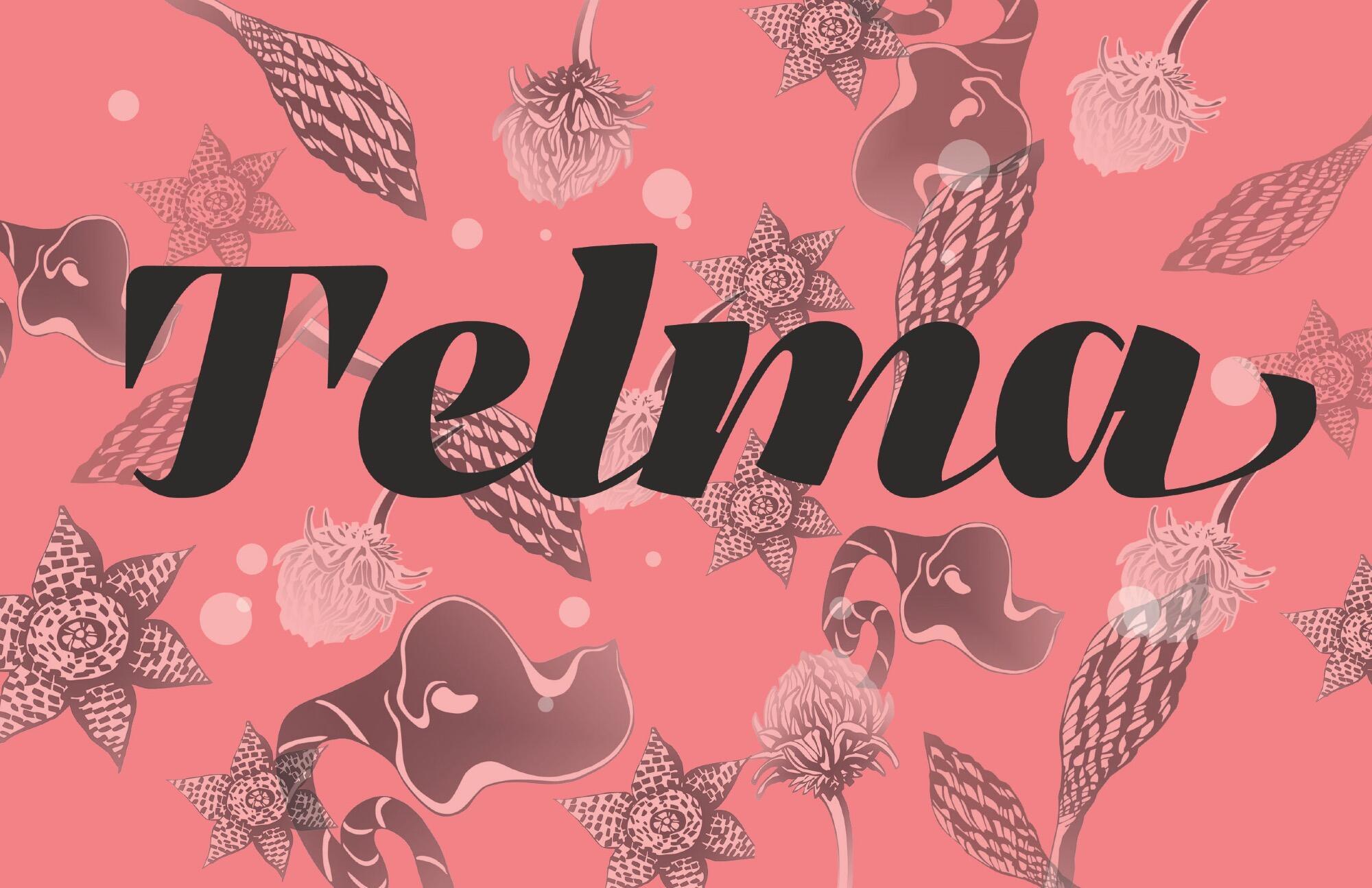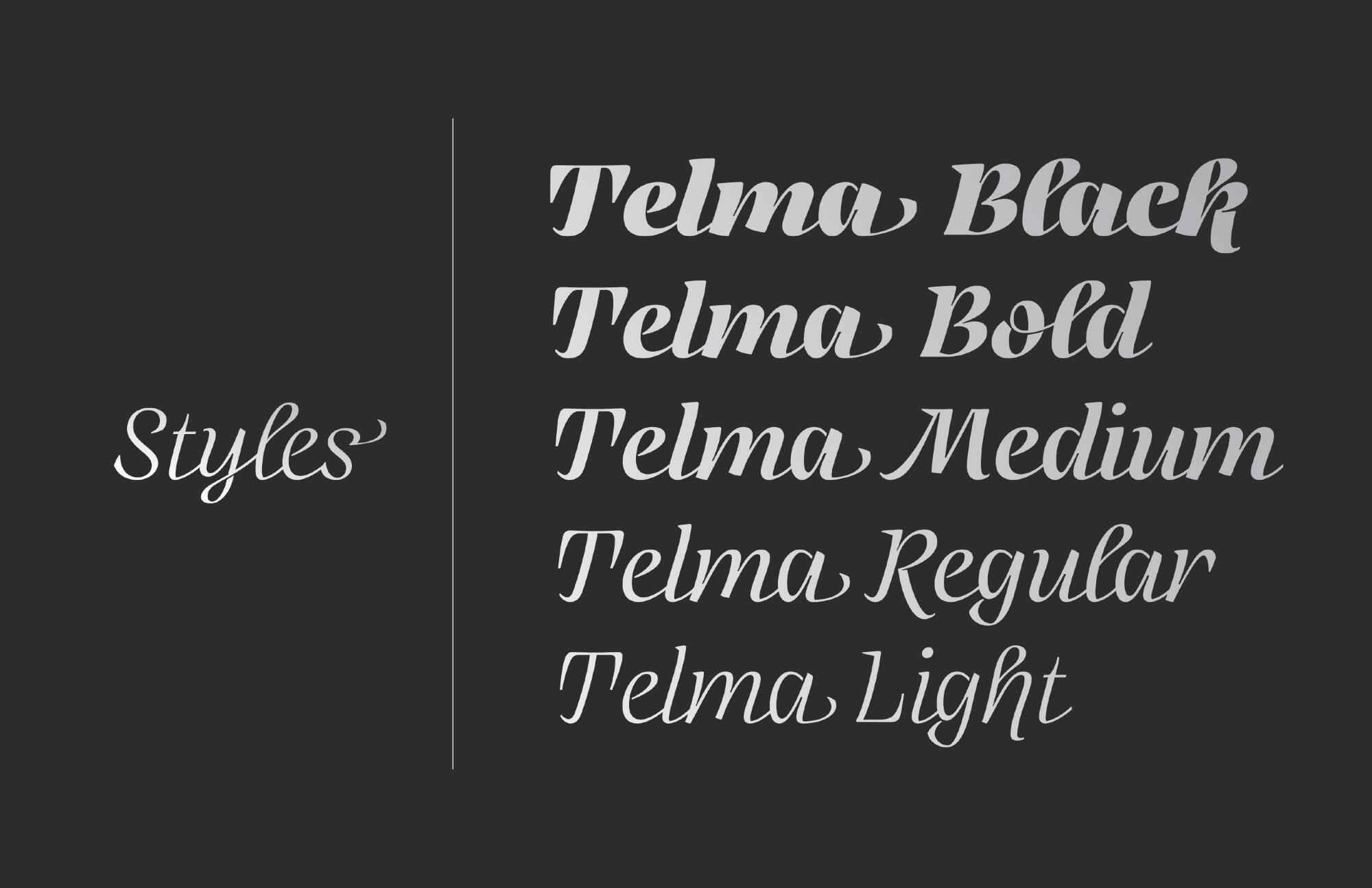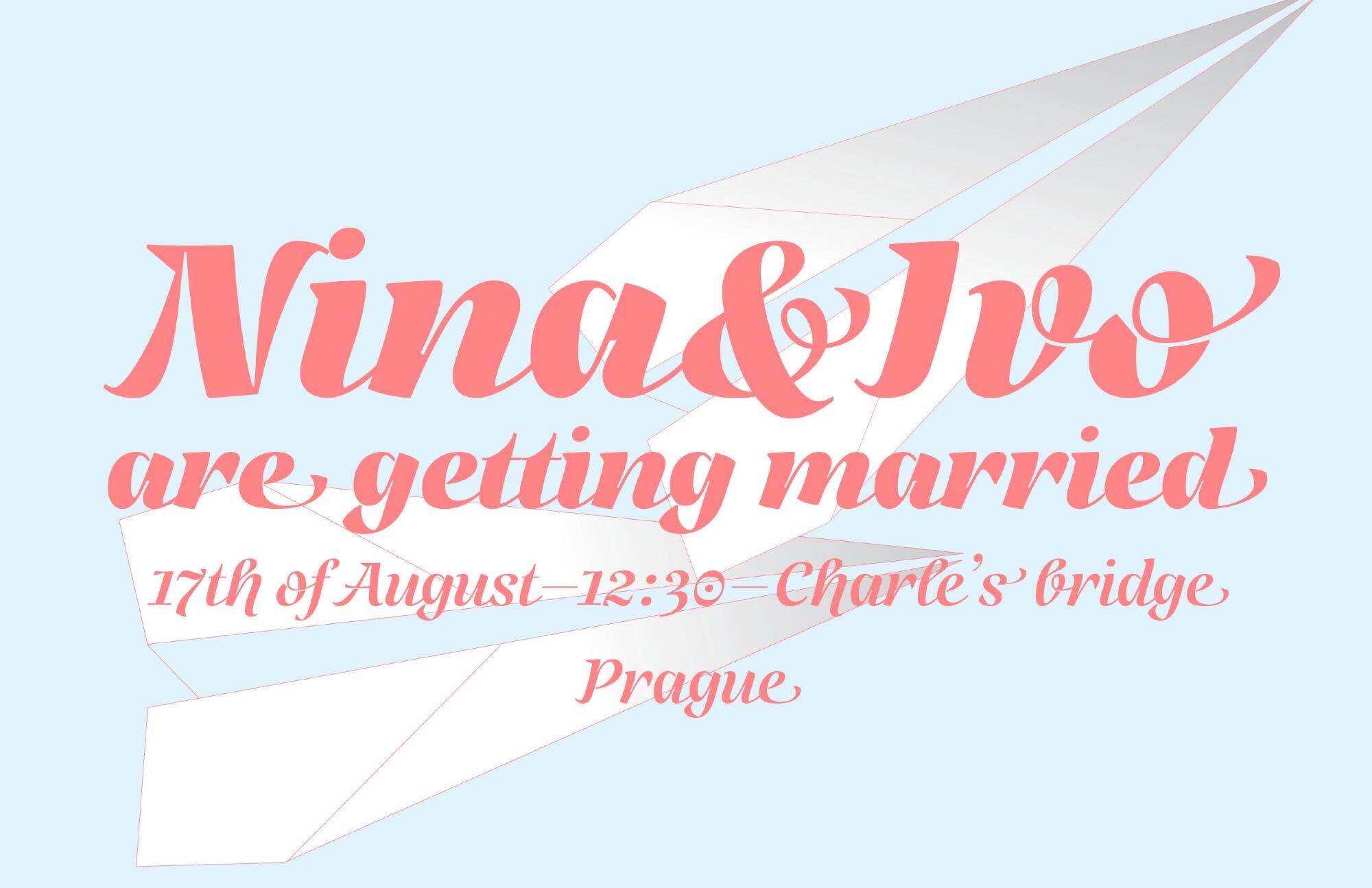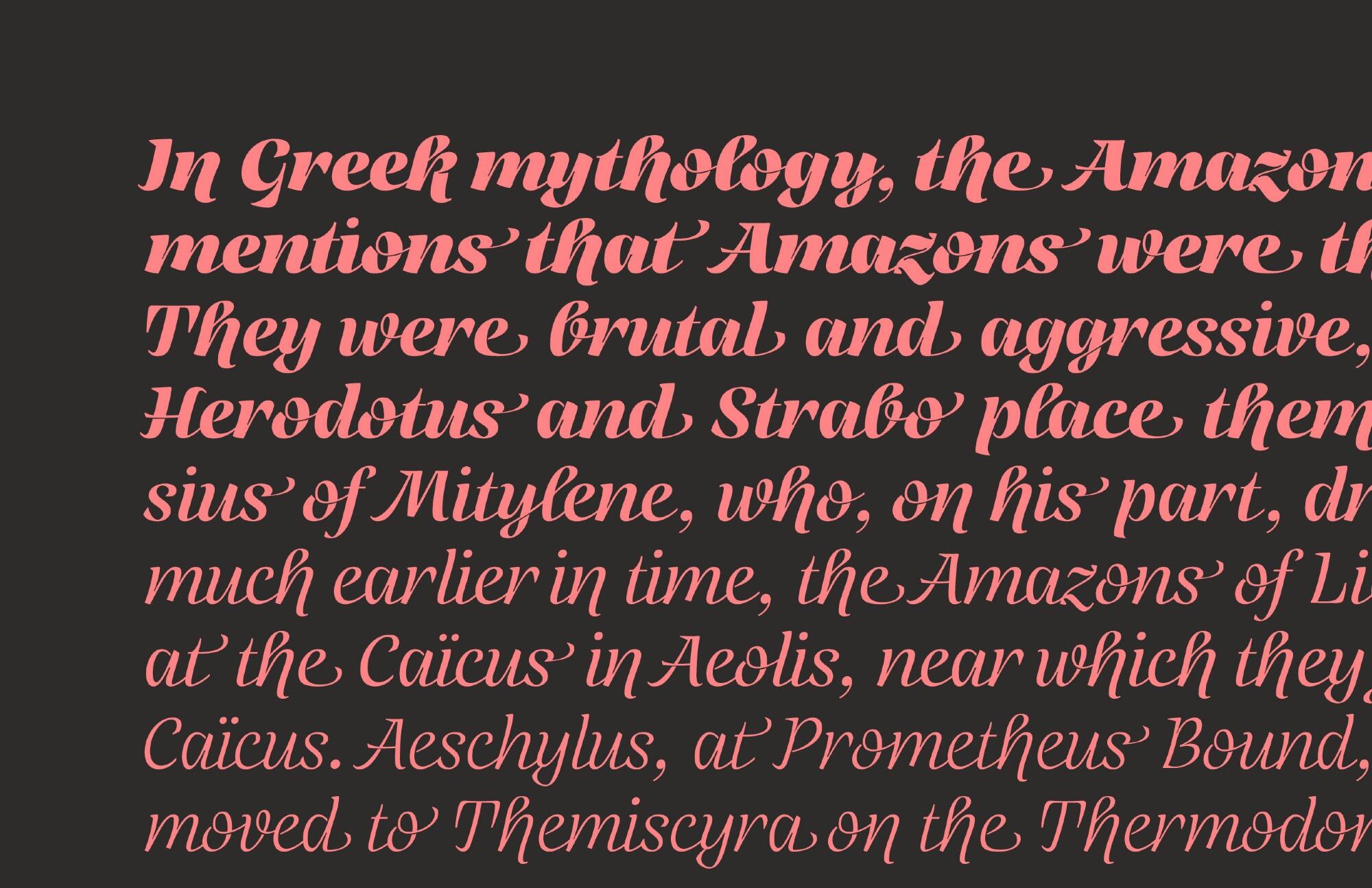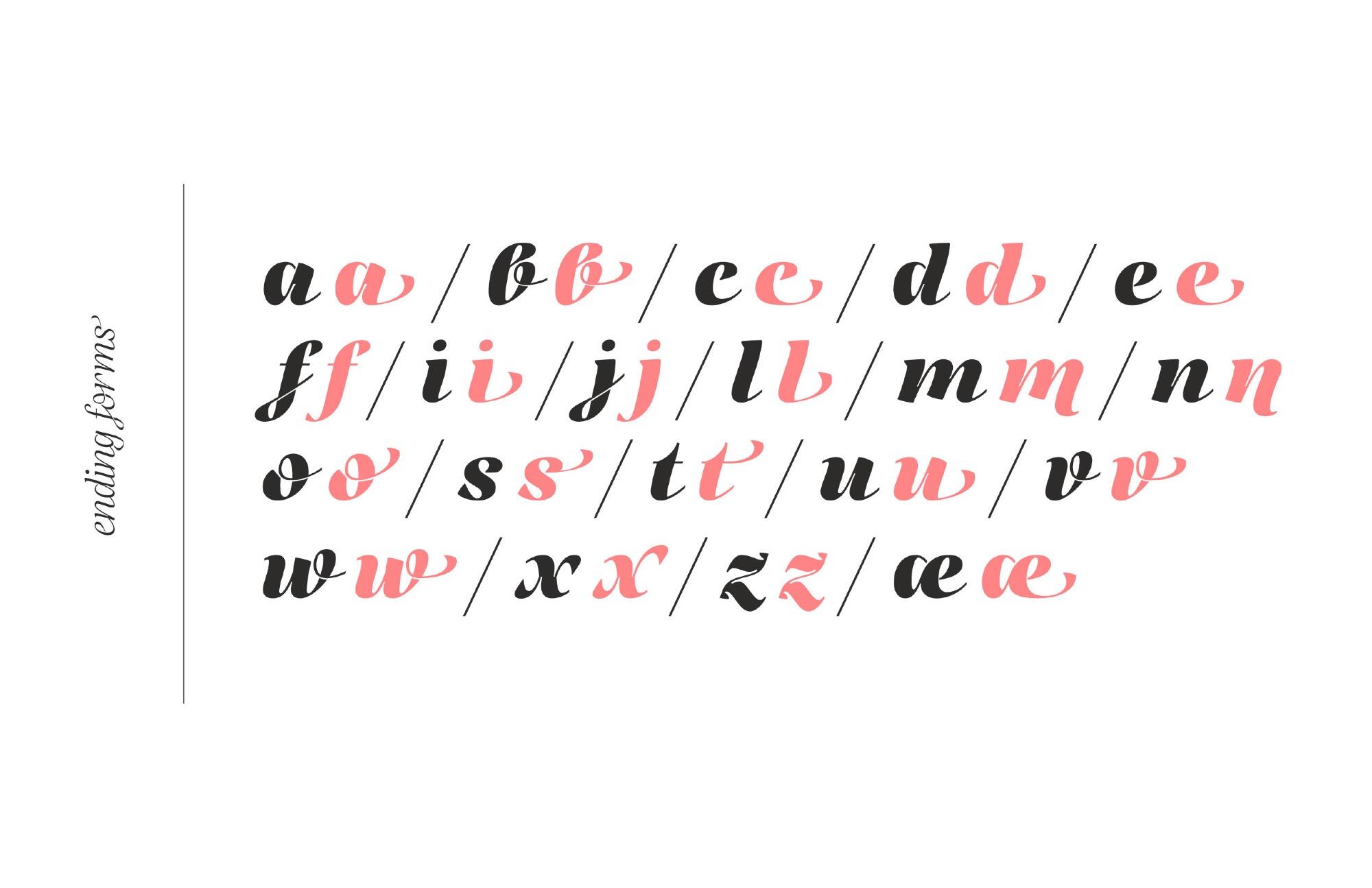
Die Telma ist eine charakterstarke verbundene Schreibschrift von Jitka Schneider und erschien 2017 über die Indian Type Foundry. Die Schrift ist heute in fünf Strichstärken bzw. als eine variable Schrift kostenlos über Fontshare erhältlich. Die Telma-Familie verfügt über eine erweiterte lateinische Belegung und Schwungbuchstabenformen für das Ende von Wörtern.